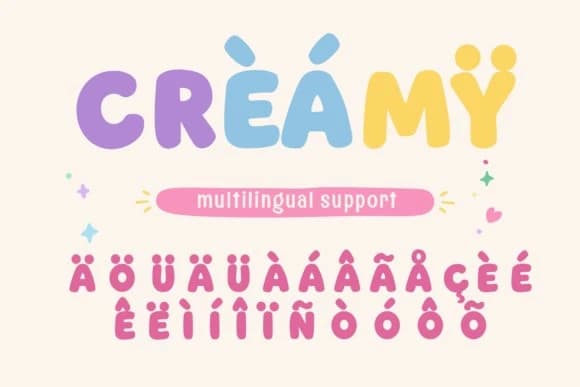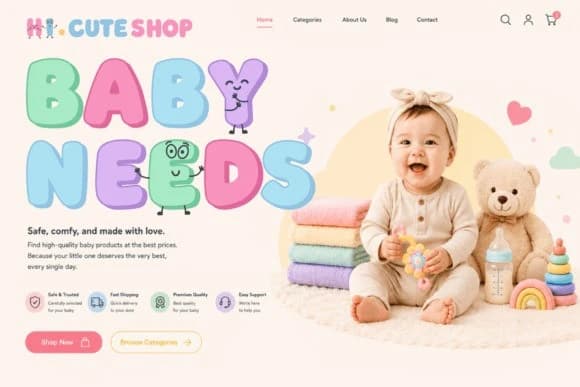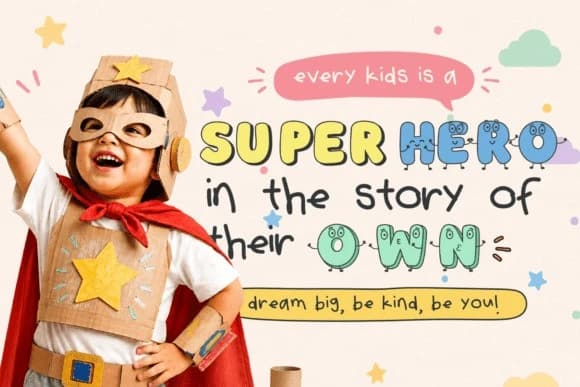
Smiley Candy Yazı Tipi
Smiley Candy Font, tipografi dünyasına neşe, hayal gücü ve oyuncu canlılık katması için tasarlanmış büyüleyici derecede çekici dekoratif bir gösterim yazı tipidir. Kawaii kültürü, animasyon sanatı, emojilerin ifadeleri ve neşeli doodle grafiklerinden oluşan canlı bir karışım.
Smiley Candy Font, tipografi dünyasına neşe, hayal gücü ve oyunbaz canlılık katmak üzere tasarlanmış büyüleyici ve çekici bir dekoratif gösterim yazı tipidir. Kawaii kültürü, animasyonlu sanat, emoji ifadeleri ve neşeli doodle grafiklerinin canlı bir karışımı.